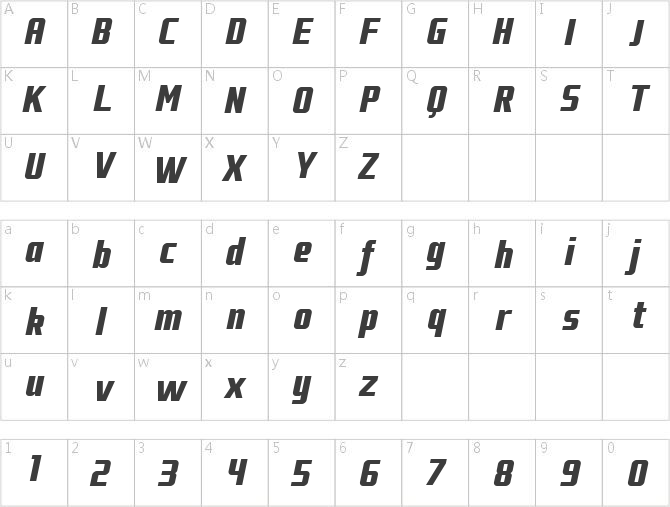
Fragma-Black-Italic
Fragma-Black-Italic介紹
Fragma-Black-Italic字體字庫是一款讓人賞心悅目、百看不厭的英文字體,適合各類廣告和產(chǎn)品包裝設計應用,字體大小0.02MB,格式為ttf字體,上傳用戶是一直在守護,作者/版權(quán)方為未知